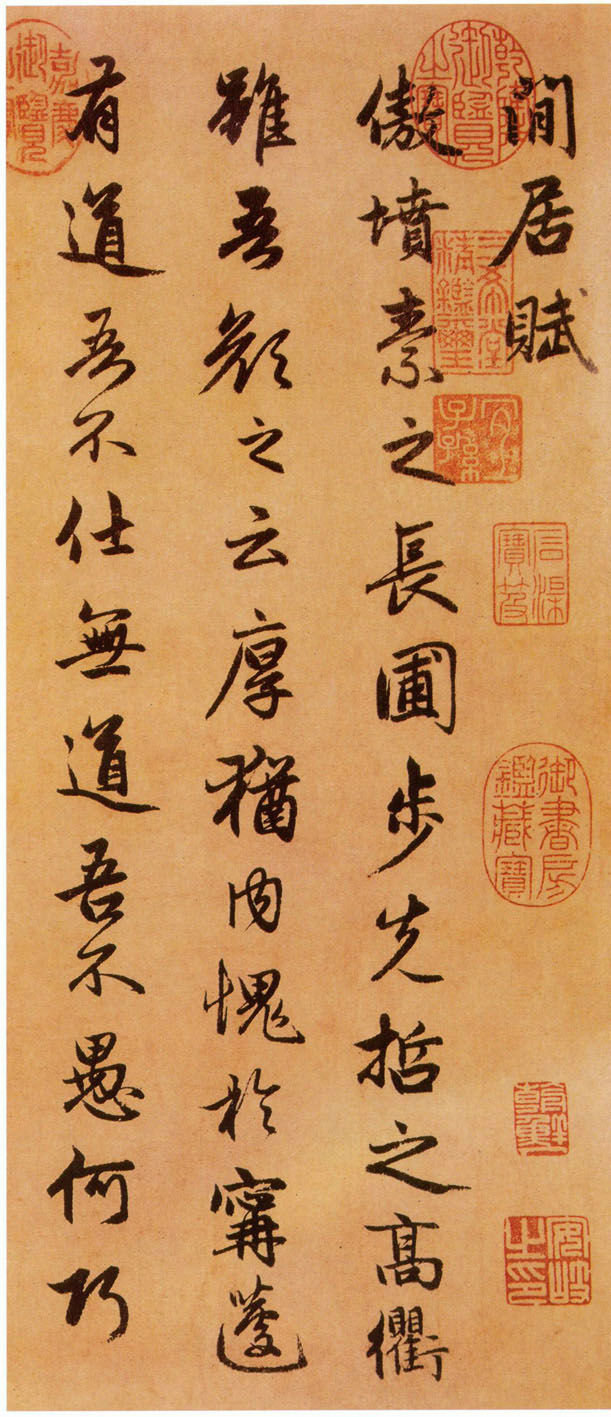
汉标赵孟頫行楷闲居赋 By 真迹小字库 商用字体
字体全名: 汉标赵孟頫行楷闲居赋
字体简介: 下载须知:本字库非标准GB2312字库。本字库只包含了赵孟頫《闲居赋》真迹上的“767个字”。详见图样。赵孟頫《闲居赋》行楷,纵38厘米,横248.3厘米,台北故宫博物院藏,书西晋著名文学家潘岳《闲居赋》一首,56行,款署子昂。此作无年款,但从书法上考察,应是晚年所书,为赵孟頫上乘之作。